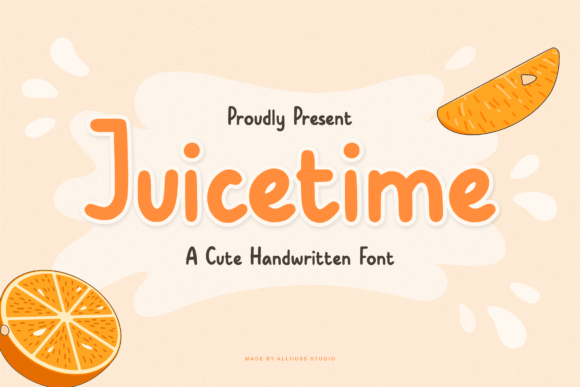
Juicetime
หากคุณกำลังมองหาเนื้อหาคุณภาพสูงเช่น Juicetime แพ็คเกจพรีเมียมนี้เป็นตัวเลือกที่ยอดเยี่ยมสำหรับโปรเจ็กต์สร้างสรรค์ของคุณ
สร้างขึ้นอย่างแม่นยำ Juicetime ให้เวกเตอร์ที่สะอาด พิมพ์ตัวอักษรที่ราบรื่น และใบอนุญาตเชิงพาณิชย์เพื่อความสบายใจ